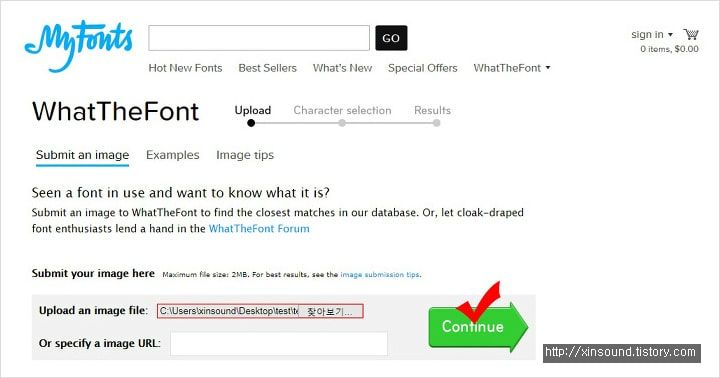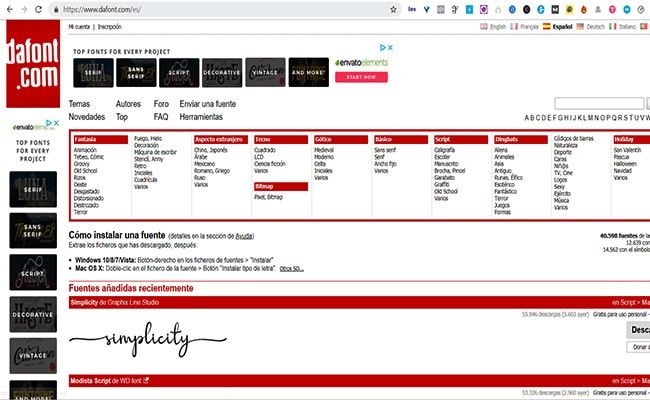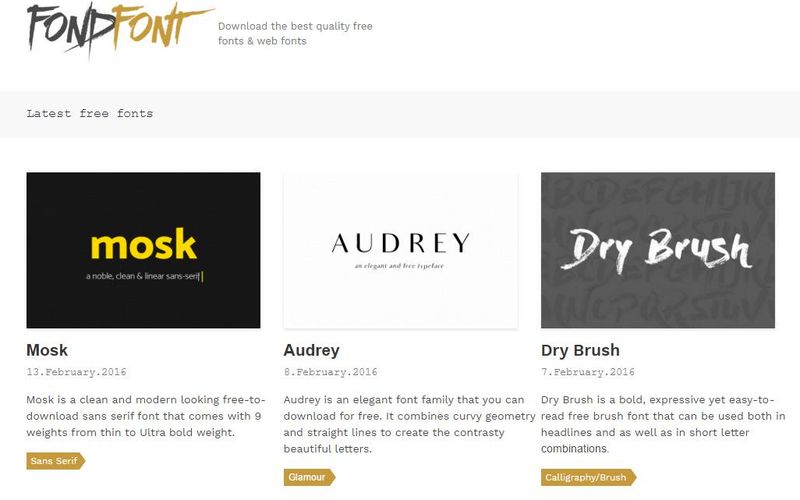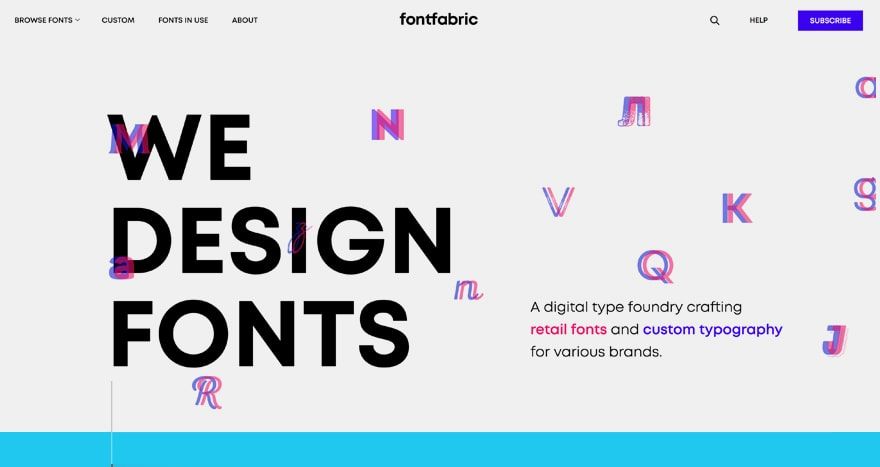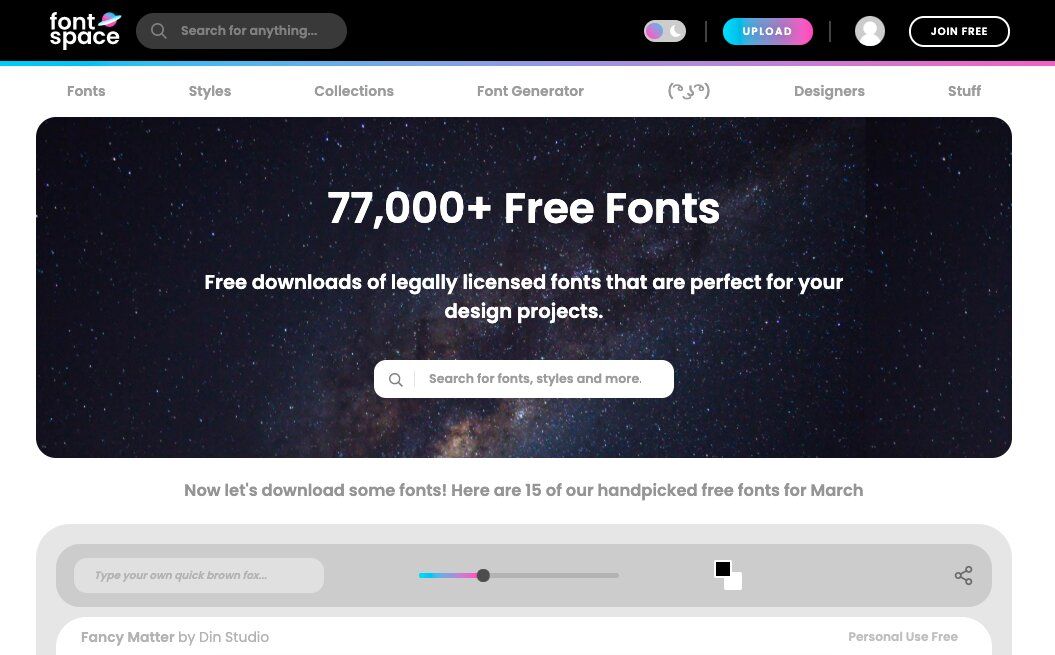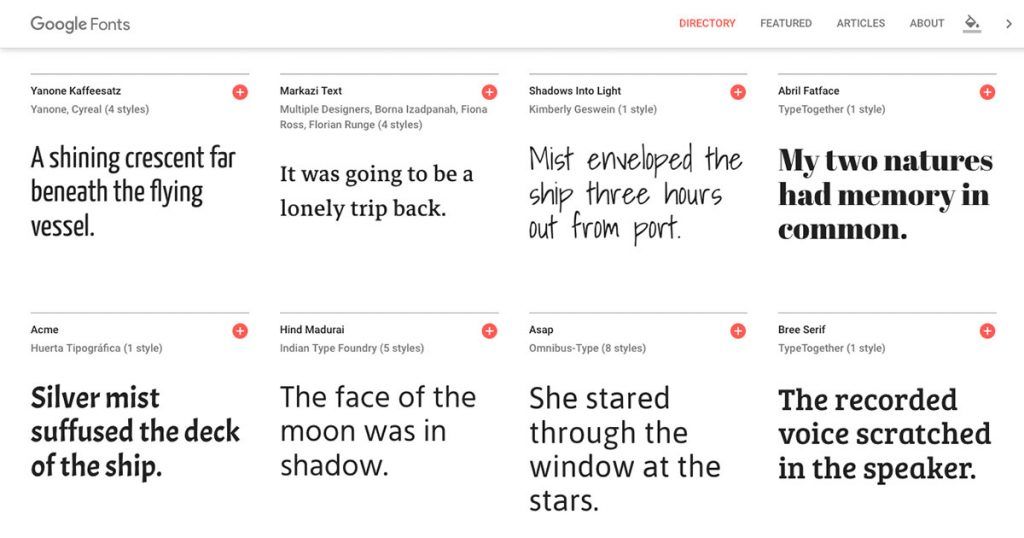
Usar tipografías bonitas, legibles y acorde a tu marca es un must para tu empresa o negocio. Tanto para promocionarte como para destacar ante tus competidores es algo que los clientes valoran y encima… ¡les gusta! No te quedes solo con lo que te proporciona el procesador de texto por defecto, ¡ve más allá! Las tipografías adicionales son fáciles de descargar en cualquier página web, gratuitas y respetando las licencias del creador. Hoy te dejamos con 10 bancos de tipografías para que encuentres las que más te gustan.
¿Por qué las tipografías son tan importantes?
Aunque no lo creas, junto al logotipo y a los colores, la tipografía es un dato fundamental para la identidad corporativa de tu empresa, para diferenciarte y transmitir tu esencia. Estamos hartos de ver siempre logos con la letra “Times New Roman”, que sí, es muy elegante, pero es muy básica; o “Comic Sans”, que parece que nos hemos quedado en la época de primaria. No nos dicen NADA. (Bueno sí, que somos un poquito basic)
Tenemos que dedicarle tiempo y buscar algo diferente, una tipografía original que nos represente como marca y tenga personalidad propia.
Muchos piensan que es una tontería, pero no, la tipografía es básica como herramienta clave del marketing digital. Algunos de sus beneficios y ventajas es que contribuye a reforzar el mensaje que estamos dando como empresa y la identidad de tu marca, como te hemos comentado.
Además, transmite diferentes tipos de sensaciones. Por ejemplo, cuando vemos una letra muy recta y “serif” nos da la sensación de formalidad. Sin embargo, la tipografía “sans serif” se considera más creativa y nos transmite dinamismo y confianza.
En este post te voy a enseñar los mejores bancos de tipografías gratuitos tan tan chulos que la gente se va a quedar pasmada con tu originalidad. ¡El sueño de cualquier diseñador!
La mayoría incluyen la opción de introducir tu propio texto para que veas como quedaría con cada tipo de fuente. Eso sí, no te hagas el loco/a y léete bien la letra pequeña (esa de la que nunca hacemos caso), porque puede que no sean gratuitos si la utilizas para uso comercial.
Bancos de tipografías gratis que tienes que conocer sí o sí
1. Google Fonts
Posiblemente sea el más conocido. Pertenece a nuestro querido amigo Google, ese que nos ayuda tanto, ¡hasta para buscar tipografías! Google Fonts te ayudará a crear y definir el estilo que quieres y las fuentes se pueden previsualizar en la mayor parte de los documentos, formatos, pantallas, etc.
Además de ser súper práctico y fácil de usar, es de uso libre y es un directorio interactivo… ¿esto que es? Pues bien, significa que las fuentes que Google Fonts tiene están disponibles para web, como si fueran universales.
De cara al SEO, Google Fonts es una muy buena opción. Tiene 916 diferentes tipos de fuente, pero si buscas algo muy específico tal vez te quedes corto/a.
Consideramos que Google Fonts es ideal para textos largos y corporativos, pero para el logo, nuestro consejo es que busques algo más original y llamativo.
NOTA OINK: 8/10
Banco de tipografía gratis Google Fonts landpage
2. DaFont
En este banco de tipografías podrás descargar más de 13.000 fuentes, con multitud de estilos, formas y categorías. Se pueden descargar fácilmente y funcionan sin ningún problema, los archivos funcionan en varios sistemas operativos como son Mac, Linux o Windows.
Una facilidad que nos dan es que se puede previsualizar la palabra o texto que tú quieras en el tipo de fuente que has elegido- Vamos, que nos dan el trabajo hecho, jeje. Además, te da la opción de crear tu propia tipografía, pero para ello tienes que tener unas poquitas nociones de diseño y conocer las herramientas que nos ofrece la propia plataforma.
Tenemos 9 categorías diferentes de tipografías modernas, como por ejemplo techno, gótico, fantasía, básico, holiday, etc.
No todo es tan bonito como parece, DaFont puede tener algunas tipografías de mala calidad y que les falte el acento así que te aconsejamos que en la frase de prueba que utilices incluyas alguna tilde, diéresis, etc para comprobarlo con antelación.
NOTA OINK: 7/10
Banco de tipografía DaFont landpage
3. MyFonts
¡Y seguimos con los bancos de tipografías gratis! Desde la creación de Shazam, la vida tiene más sentido, es otro “rollo”. Estar tranquilamente escuchando una canción que te guste y con solo un click saber su título y su intérprete es IDEAL. Pues ahora, han creado MyFonts, que es lo mismo pero con tipografías. Una herramienta SUPER útil llamada “What the font”.
Simplemente, subes la imagen con el texto que quieres saber y ¡magia! Te dice la tipografía con la que ha sido escrito. Además, MyFonts nos brinda más de 130.000 tipografías de muy buena calidad y muy variada.
NOTA OINK: 8/10
como identificar una tipografía de imagen en app MyFonts